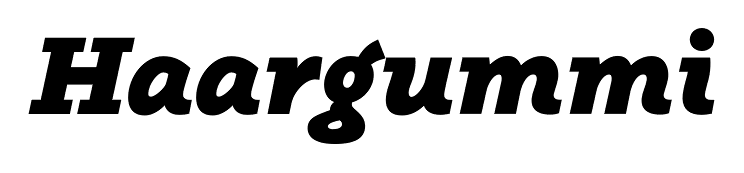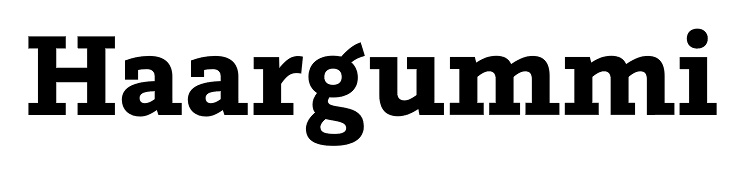
Meinungen zur Graublau Slab
ein paar dinge, die mir aufgefallen sind bzw. die ich mich gefragt habe:
das ›a‹ ist oben links ziemlich geschlossen. ich hätte die serife kürzer gemacht. auch das ›m‹ ist ziemlich voll innen. da hätte man abhilfe schaffen können, ohne den slab-charakter aufzugeben. die jeweils zweite form ist von mir:
schade auch, dass es kein alternativ-›g‹ gibt. mir ist schon klar, dass dieses ›g‹ das markenzeichen der schriftart ist, aber wenn man sich einzelne wörter groß anschaut, kann es durchaus wie ein fremdkörper wirken.
das kursive ›r‹ kommt mir in den fetten schnitten etwas übergewichtig in puncto strichstärke vor. außerdem verstehe ich nicht ganz, warum das ›a‹ in diesen schnitten eine delle hat. wirkt auf mich eher schräg als schick:
und sehe ich das richtig, dass die hoch- und bruchziffern dicktengleich sind? wenn ja, frage ich mich, ob das einen sinn hat, den ich nicht sehe. in jedem fall ist es schade, dass die serifen, mit denen ja sonst nicht eben sparsam umgegangen wird, hier komplett fehlen.
angenehm finde ich, dass kombinationen wie ›fl‹ und ›fk‹ auch ohne ligatur nicht zusammenstoßen. schön ist auch, dass die kapitälchen nicht, wie in vielen anderen schriften, zu klein geraten sind, aber ich würde ihnen in den schriftmustern einen hauch mehr laufweite geben, um sie besser wirken zu lassen. und apropos schriftmuster: im pdf auf seite 7 stehen die beschriftungen wohl versehentlich nicht auf derselben linie wie die beispiele.
Eigentlich eine schöne Schrift … aber,
das kursive r geht überhaupt nicht. das kurs. g auch nicht, die beiden nebeneinander :neenee:
Das kleine g fällt aus dem Rahmen, es wirkt zu leicht und etwas verkümmert. Auch das kleine r befreidigt mich nicht, man hätte hier die rechte Seite ähnlich ausbilden können wie das a oben, also mit Serife.
Die kursiven f sind schön.
Die Unterlängen der y wirken zu kurz. v.a. in den Kursiven.
Das kursive V und W mit der Biegung ist seeeeehr gewöhnungsbedürftig. Die Gewichtsverteilung bei A, V, Y, M, N sind m.E. ungelöst. Die aufrechten M kippen nach links. Die S in den fetteren Schnitten sind zu klein.
Klar, andere aktuelle Slabs wie Adelle und Bree Serif kommen viel gleichförmiger daher. Aber aus exakt diesem Grund, braucht die Graublau Slab ja nicht so aussehen. Die Graublau Sans ist ja auch nicht deshalb erfolgreich, weil sie die Kievit von fonts.info ist, sondern weil sie ihren ganz eigenen Charakter hat.
Für die Graublau Slab gilt das Gleiche. Sie passt nicht auf jede Gestaltungsaufgabe, aber wo sie passt, werden gerade die Eigentümlichkeiten genau richtig sein.